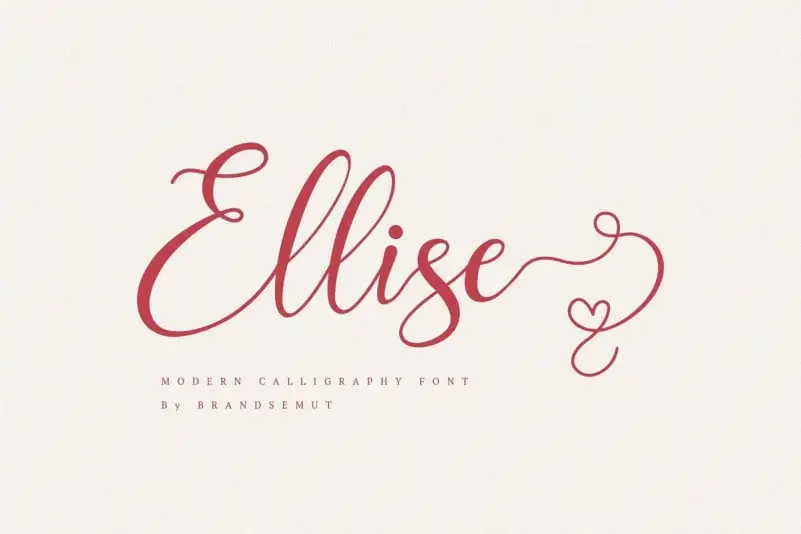
A ‘Ellise Calligraphy Font’ é uma opção perfeita para quem busca um toque moderno e romântico em seus projetos de design. Essa fonte script não só oferece um charme natural, como também ligaturas e alternativas criativas que tornam seu trabalho ainda mais especial. É a escolha perfeita para aqueles buscando uma textura elegante que enriquece qualquer projeto gráfico. Com o ‘Ellise Calligraphy Font’, sua criação adquire um toque refinado e feminino, transformando cada detalhe em algo único e bonito. Este é mais do que simplesmente uma fonte; ele é a essência de uma paleta de sensações sutis que podem ser usadas para transmitir emoções através da palavra. Perfeito tanto para projetos pessoais quanto profissionais, este ‘Ellise Calligraphy Font’ será seu parceiro ideal em qualquer projeto onde desejará expressar elegância e romantismo. Sua facilidade de utilização torna-o uma opção versátil que pode ser adaptada ao estilo único do design gráfico, garantindo um resultado final personalizado e impressionante.